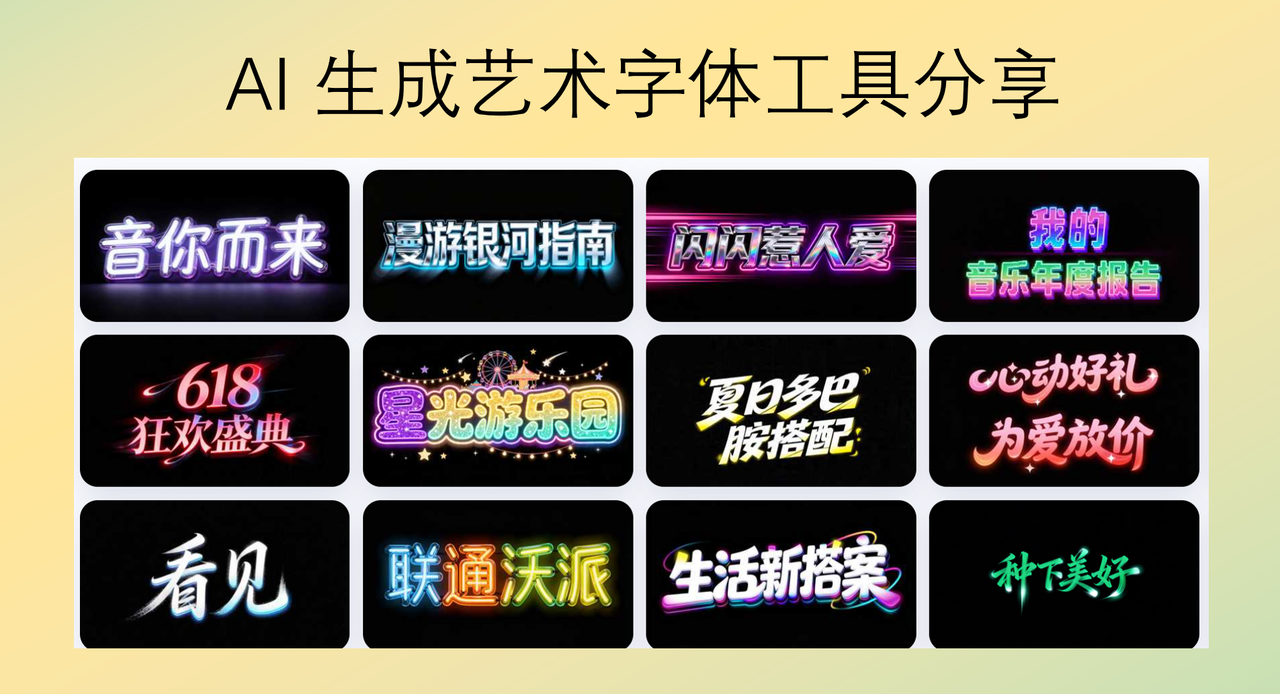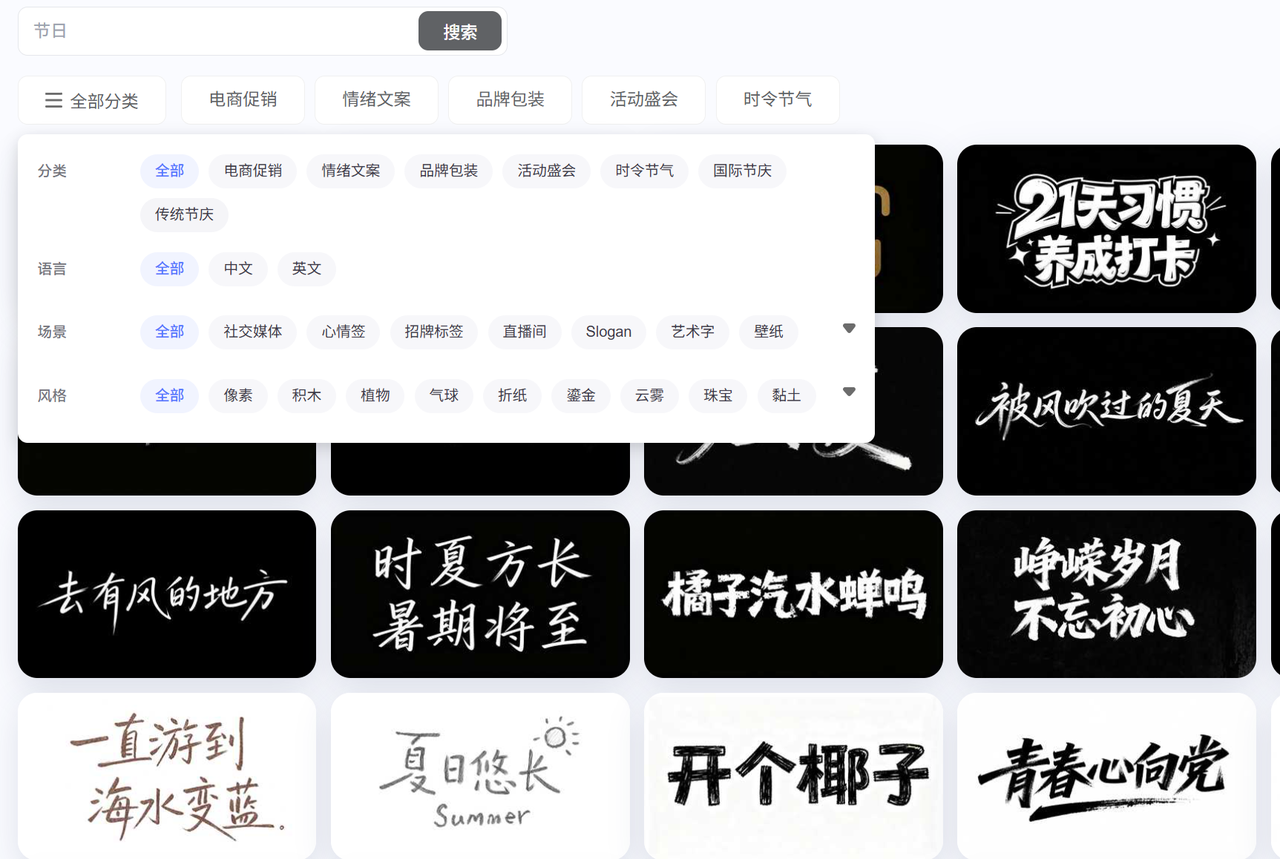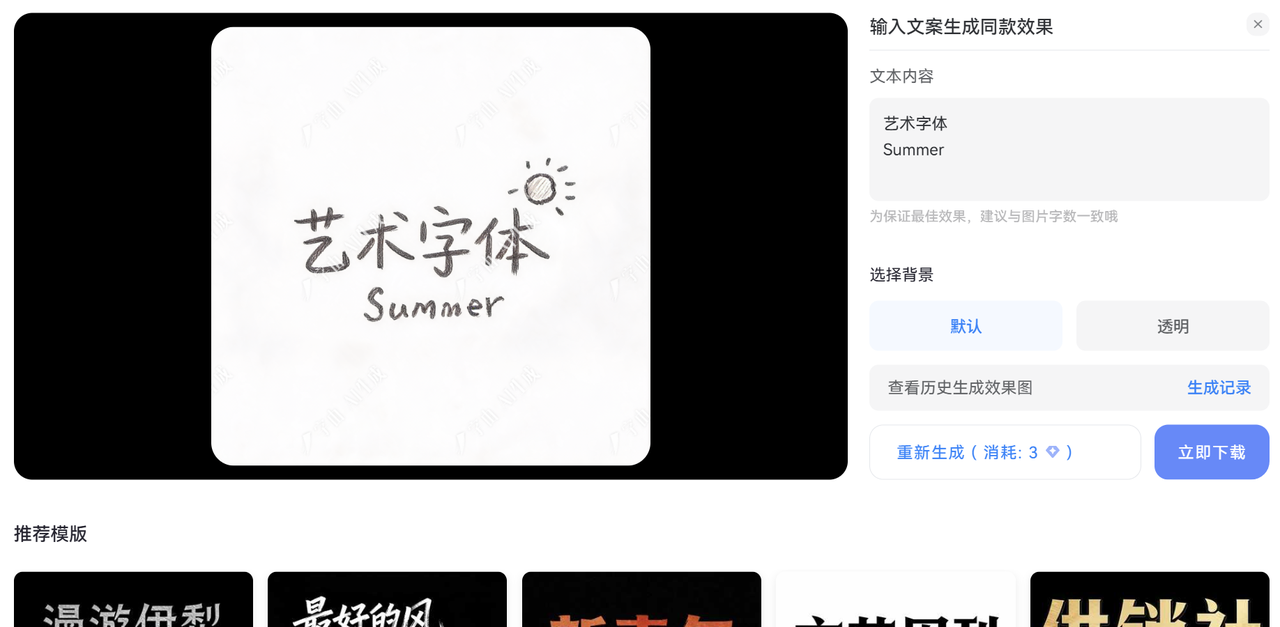
AI 生成艺术字体工具分享?字由 AI 字体推荐
很多设计师面临两个难题:一是缺乏足够的时间手工设计字体,二是难以找到既美观又符合需求的现成字体。传统的手绘或找设计师定制艺术字体的方式不仅耗时,而且成本高。我尝试了几个AI生成艺术字体工具,节省了不少时间和精力。这篇文章将分享我的使用体验,推荐几款实用的AI工具,并分析它们如何帮助设计师提升效率。
字由AI字体
在众多AI生成艺术字体工具中,字由AI字体界面简洁,操作直观,完全不需要专业设计背景也能上手。
字由AI生成艺术字体流程
打开字由AI字体页面,根据自己的使用场景,选择艺术字体分类或者搜索相关关键词
选择一个合适的模板,输入自己的文字,点击一键生成,即可完成一键生成。
整个过程操作简单,不用设计基础,小白也能快速生成。
操作流程简单高效
打开网站后,我只需输入关键词(如“复古”“未来感”“手写”),系统就会生成一组风格相近的字体样式。选择一个合适的模板,输入自己的文字即可完成一键生成艺术字体。
风格选择丰富
字由AI字体的最大亮点是风格多样性。从简约现代到水墨国风,从几何抽象到手写涂鸦,几乎能满足不同场景需求。
实用性强,适合初学者
对于刚入门的设计者来说,字由AI字体降低了学习成本。它不需要复杂的参数设置,也无需担心版权问题。
其他3款值AI生成艺术字体工具
1、FontStruct
FontStruct 是一款开源工具,允许用户通过拼接模块化部件创建字体。虽然操作稍复杂,但它能实现高度定制化。比如,我曾用它制作一套带有齿轮纹理的工业风字体,满足了客户的特殊需求。
2、Fontjoy
Fontjoy 的特点是“一键生成”功能,输入关键词后,系统会自动推荐多组字体组合。我曾用它为一家初创公司设计logo,快速筛选出3套备选方案,大幅缩短了决策时间。
3、TypeDraw
TypeDraw 提供丰富的动画选项,比如字体变形、渐变色彩等。我曾用它为视频广告设计动态标题,效果比静态字体更具吸引力。
AI生成艺术字体工具的实用价值
通过使用字由AI字体和其他平台,我深刻体会到AI工具对设计工作的助力。它们不仅节省时间成本,还能激发创意灵感,帮助用户突破传统设计的局限。
对于设计师而言,掌握这类工具意味着:
- 提升工作效率:减少重复性劳动,专注于核心创意;
- 拓宽设计思路:接触更多风格可能性,打破固有模式;
- 适应市场需求:快速响应客户反馈,灵活调整设计方案。
当然,AI工具并非万能,但它们无疑是现代设计不可或缺的伙伴。无论你是初学者还是资深从业者,找到适合自己的工具,都能让设计过程更加轻松高效。还能探索更多可能性。希望这篇文章能为你提供实用参考,助你在设计路上走得更远。